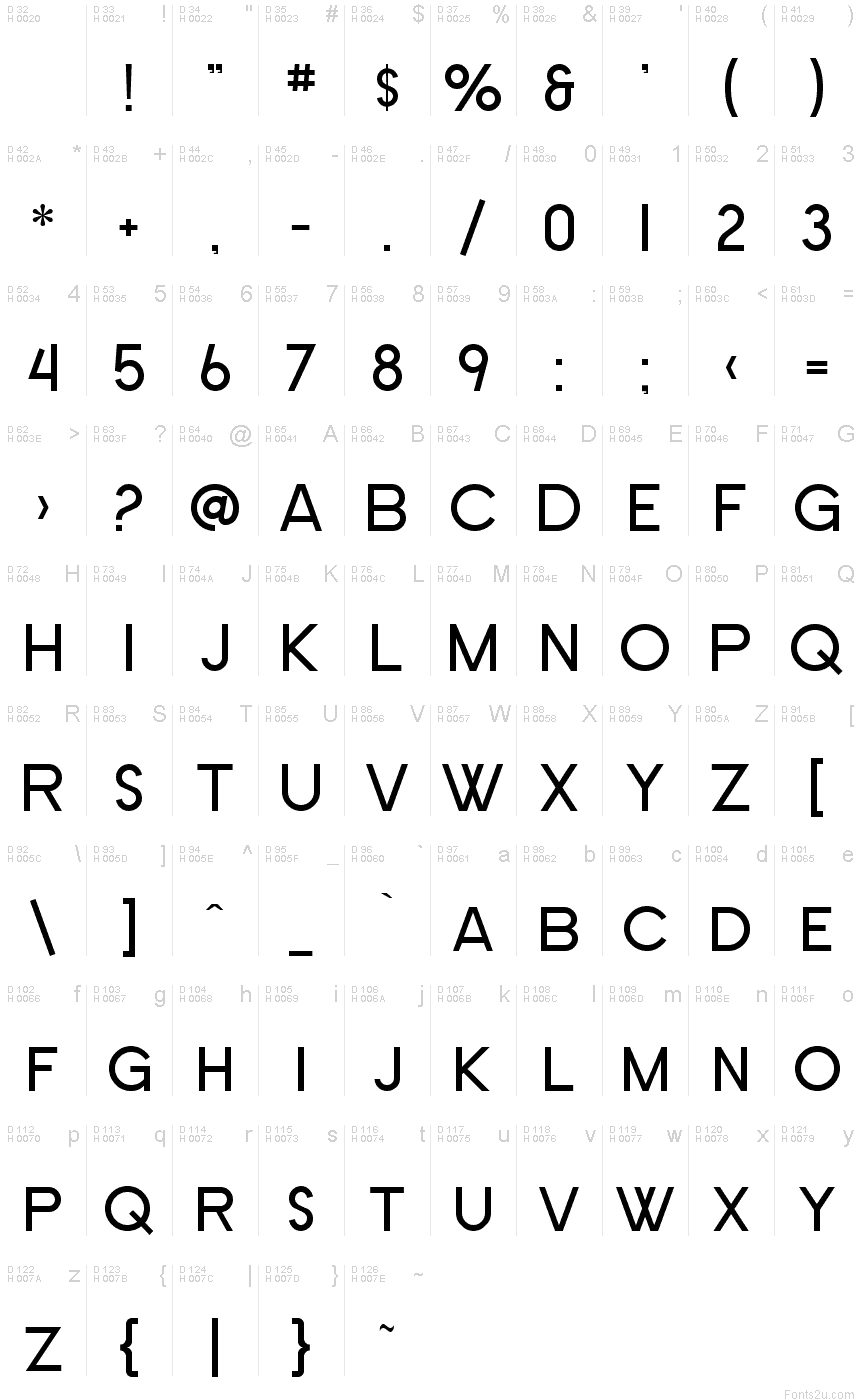
SF Old Republic SC هو خط هندسي مجاني بلا زوائد من تصميم Shywedge عام 1999. يتميز بالهدوء البسيط واللمسة المستقبلية (ريترو-فيوتشرستيك) التي ميزت رسومات الخيال العلمي في أواخر القرن العشرين. تعتمد الحروف على دوائر واسعة ومنحنيات مفتوحة وزوايا مربعة، مما يمنح الخط إيقاعاً هندسياً انسيابياً يبدو سينمائياً أكثر من كونه محايداً.
وهذا يجعله خياراً طبيعياً لعناوين الملصقات، وتصميم هوية الألعاب، ونصوص الأغلفة من عصر الـ DVD، ورسومات واجهات سفن الفضاء، وتصاميم الشعارات القصيرة، حيث يساعد هذا الخط المجاني بطابعه النظيف والتأملي على ضبط المشهد بسرعة. استخدمه للعناوين، أو أسماء الفصائل، أو المونوغرامات المدمجة عندما تريد أن تبدو الأحرف الكبيرة أنيقة واصطناعية وتفيض بلمسة من الحنين إلى الماضي.
SF Old Republic SC